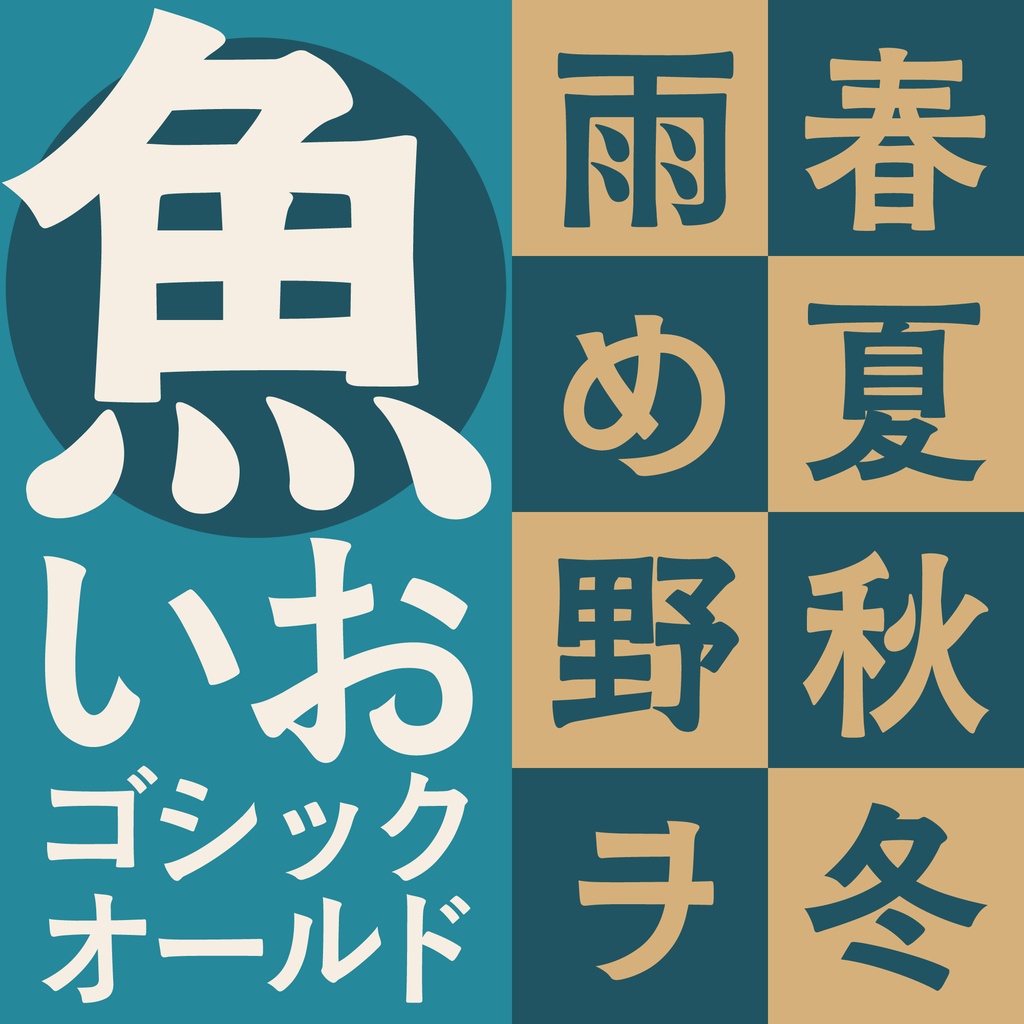
※フォント形式はttfです ■書体概要 いおゴシックオールドは、「築豊35ポイントゴチック」で表現した活版印刷の肉付きの感覚を、現代的な視点で見つめ直した書体です。 ゴチック体からゴシック体へと時代が移り変わる中で生まれた骨格の変化を、静かな佇まいと統一されたエレメントで再構築しました。落ち着きのあるトーンが、見出しにも本文にも柔らかく馴染みます。 ■収録漢字 通常版:ひらがな・カタカナ、一部役物、小学四年生までの漢字662字(今後のアップデートで拡張します) おためし版:ひらがな、カタカナ、一部役物 ※どちらもライセンスに違いはなし(商用利用可能) ■ご利用にあたり 文字魚/Typographishのフォントデータ(以下、本ソフトウェア)は本契約に定める条件でご購入者様に使用する権利を許諾します。本ソフトウェアの著作権その他一切の権利は文字魚/Typographishに帰属します。 使用条件 1)購入者は本ソフトウェアを、本人が使用する1台までのコンピューターにインストールして使用することができます。事務所など複数人で使用する場合、コンピューターの台数分のライセンスをご購入ください。 2)印刷物に使用できます。(書籍・ポスター・看板など) 3)立体制作物に使用できます。(Tシャツ・雑貨・記事など) 4)放送・映像やWEBの制作物でアウトライン化または画像化した上で使用できます。(TV・CM・映画・DVD・ゲーム・アプリ・WEBサービス・電子書籍・動画配信・SNSなど) 5*)タイトルデザイン・ロゴマークの作成に使用できます。(*商標登録は不可) 6)Canvaなどオンラインデザイン制作ツール上にフォントをアップロードして使用することがきでます。ただし使用者1名、PCまたはタブレットなど1台の使用に限ります。 禁止事項 1)本ソフトウェアを第三者に譲渡・貸与・配布・販売することはできません。 2)本ソフトウェアを元に新たな類似または同一のフォントデータを作成すること。 3)本ソフトウェアをWEBフォントとして使用すること。 4)本ソフトウェアをハードウェアに組み込みすること。 5)本ソフトウェアを使用して商標登録をすること。 免責事項 本ソフトウェアを使用して発生した如何なる問題についても、文字魚/Typographishは責任を負わないものとします。万一、本ソフトウェアが原因で使用者および第三者に損害を及ぼしてもすべて使用者が責任を負うものとします。 保証範囲 1)本ソフトウェアに著しい誤字などが発見された場合は、修正に努め修正アップデートの情報は販売ページで告知します。修正アップデートの追加料金は不要とします。 2)本ソフトウェアのインストールに伴う技術的なサポートはいたしません。 その他 上記に記載されていない条項に関しては、著作権法及び関連法規に従うものとします。 2025/07/28 Ver1.000 2025/07/28 Ver1.001 バグ修正 2025/07/29 Ver1.002 adobe系ソフトで認識されない問題を修正 2025/11/24 ver1.003 小学4年生漢字202字を追加 Copyright (c) 2025 Typographish All Rights Reserved.